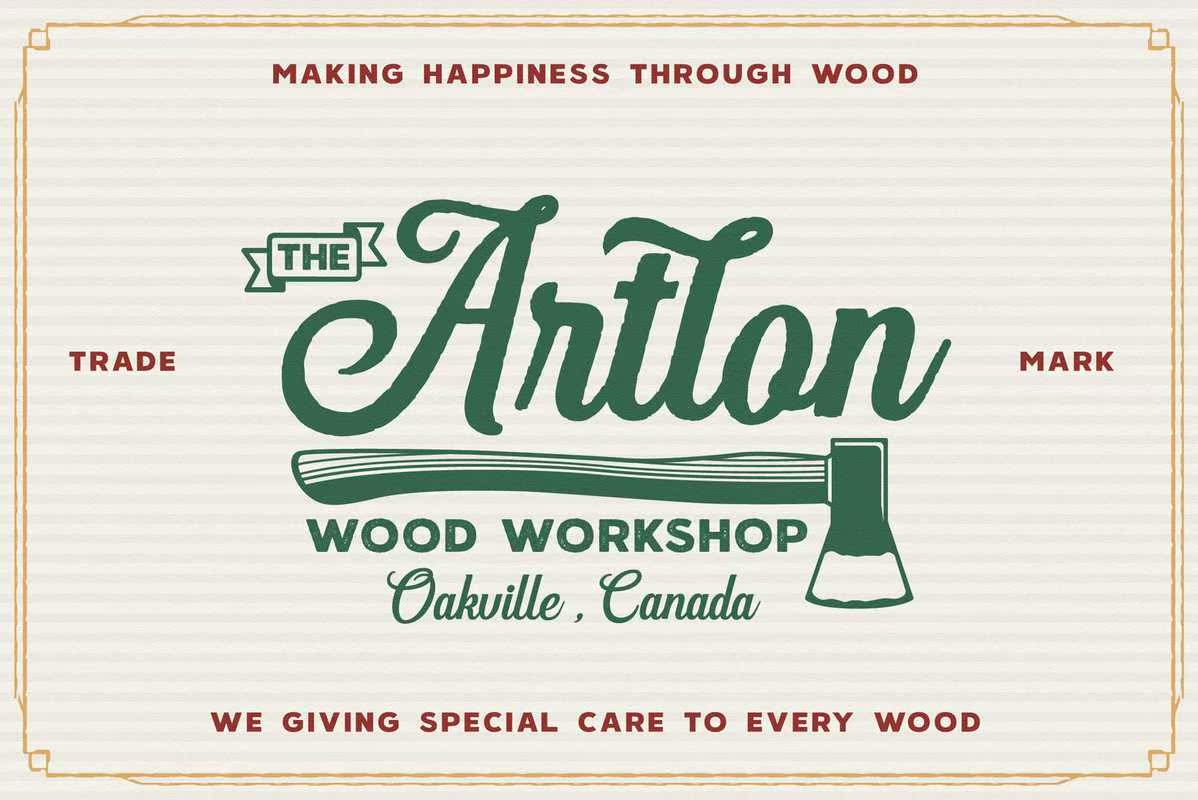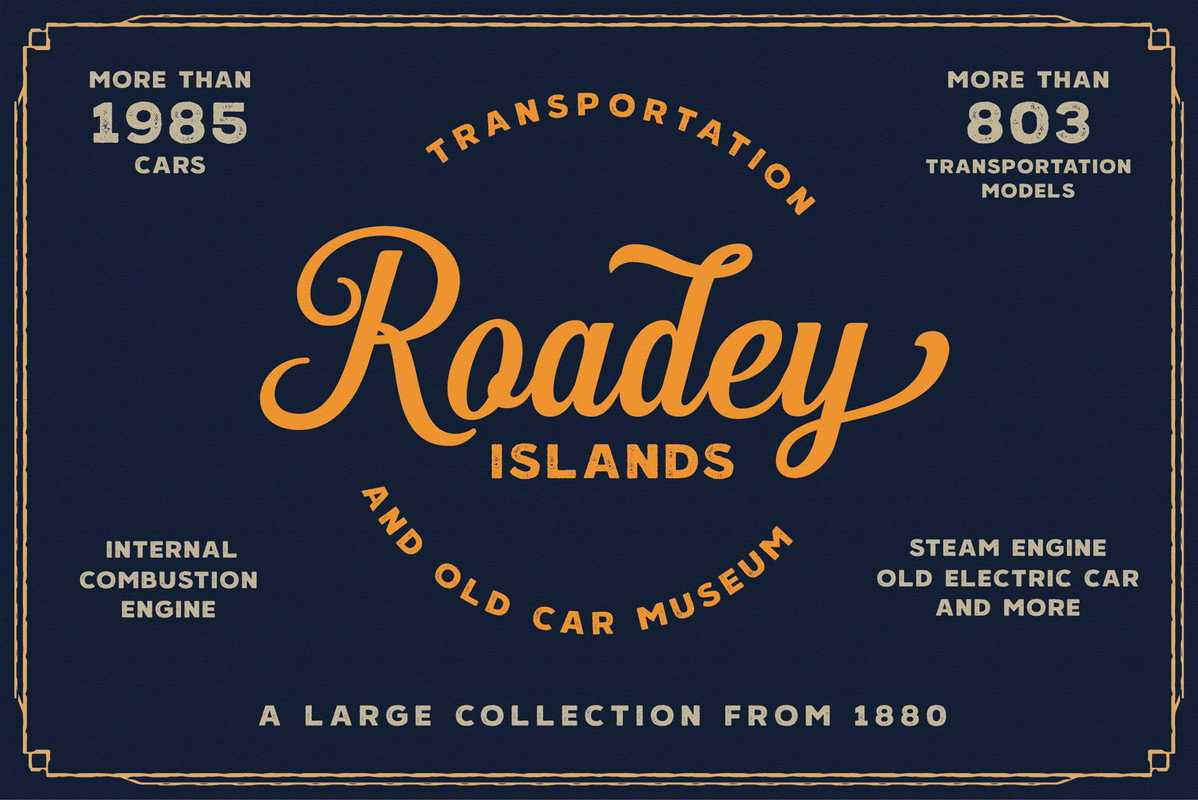
HanlethFonts是脚本和所有Capsans的组合。HanlethScript是干净的和完整的版本。HanlethHands是干净的和有年份的版本。HanlethHands是有52个年份的版本。这两个版本都是由古老的年份描述和现代风格的少量打磨而成的。HanlethScripts是一些使其独特和传奇的世外桃源SPACKAGE包括12个可编辑的徽标。HanlethFontSPACKAGE适用于Kellogo、产品包装、标题、海报、商品、社交媒体和贺卡。此免费赠品仅包含HanlethScript!HanlethFontsis是脚本和所有Capsans的组合。HanlethScript是干净的和完整的版本。HanlethHands是干净的和有年份的版本。HanlethFontsis是有52个葡萄酒学家的。这两个组合是由古老的葡萄酒描述和现代风格的少量打磨而成的。HanlethScript是一种具有独特性和传奇性的世外桃源。T他的软件包包括12个可编辑的徽标。HanlethFontsPackages适用于Kellogo、产品包装、标题、海报、商品、社交媒体和贺卡。此免费赠品仅包含HanlethScript!